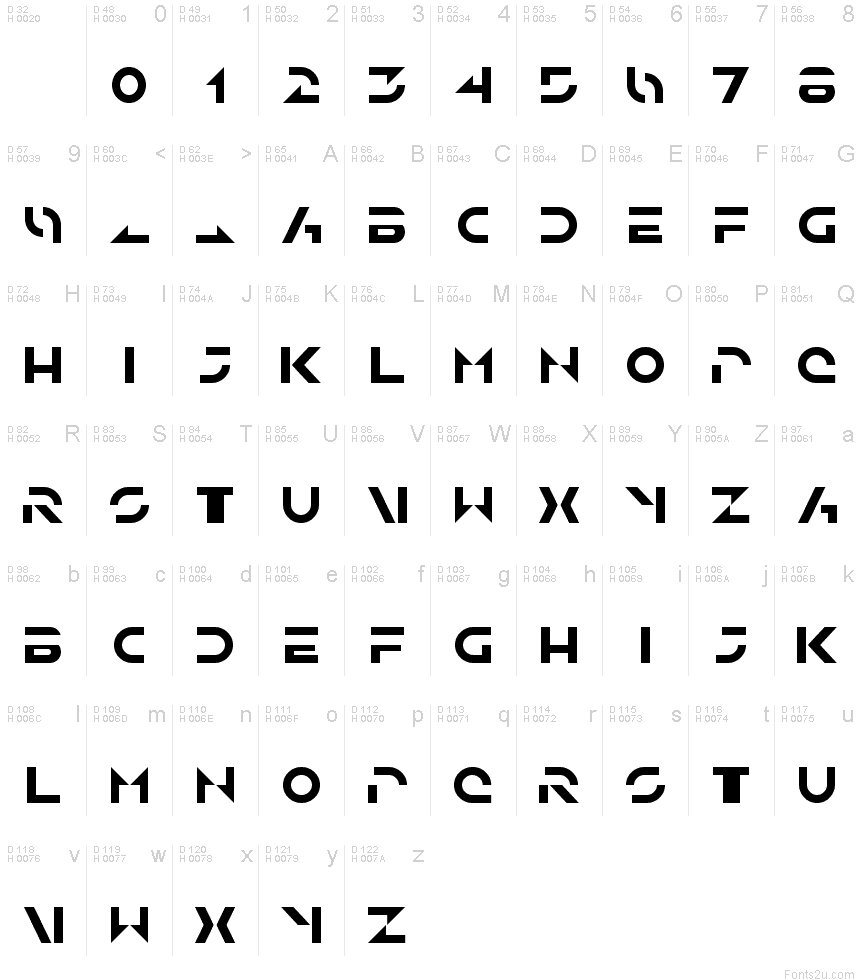
Solar Sailer, bezplatný futuristický display font od ShyWedge z roku 1999, se naplno noří do estetiky pozdní digitální éry a sci-fi. Písmena jsou sestavena z tlustých geometrických tahů a náhlých řezů, kde se zaoblené rohy střetávají s ostrými diagonálami, což fontu dodává aerodynamický a mechanický nádech připomínající prostorovou grafiku éry herních konzolí.
Hodí se pro titulky plakátů, herní loga, klubové letáky, technologické ziny a grafiku obalů, kde hledáte výrazný syntetický hlas namísto neutrálního nadpisu. Jelikož jde o font zdarma, dává smysl i pro titulní karty, krátké texty na obálkách a monogramy – právě ty oříznuté spoje a kruhové tvary vyniknou nejlépe ve stručných formátech s vysokým dopadem.